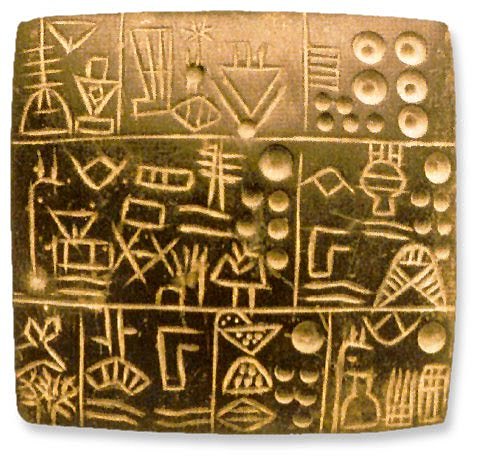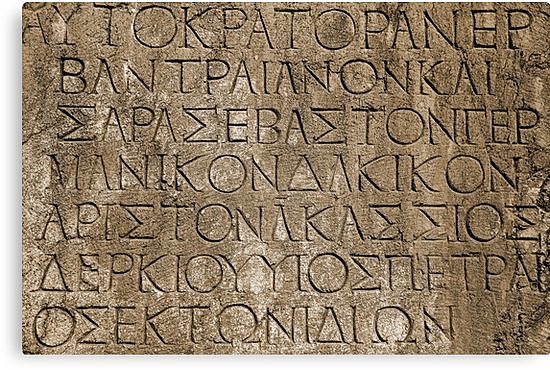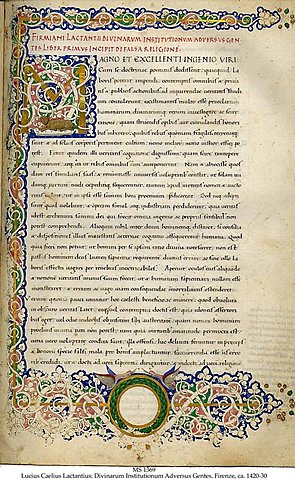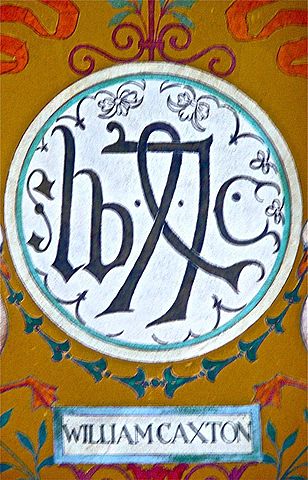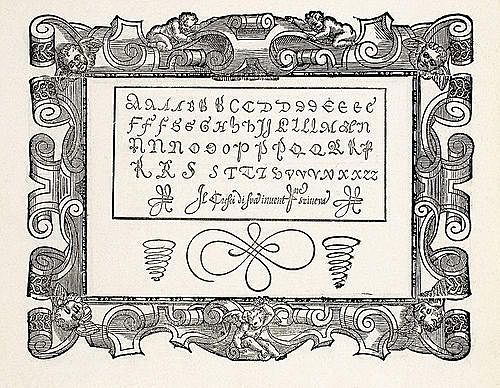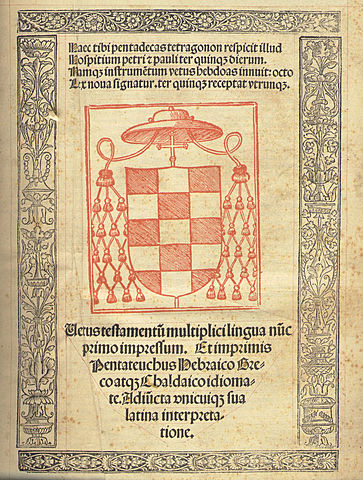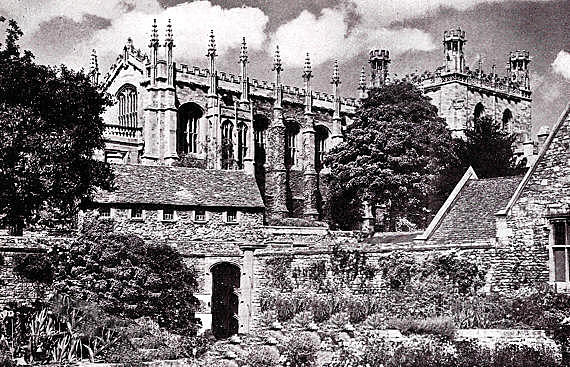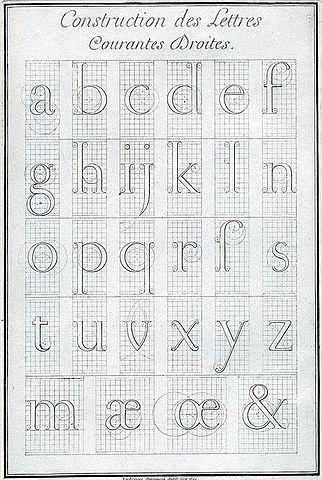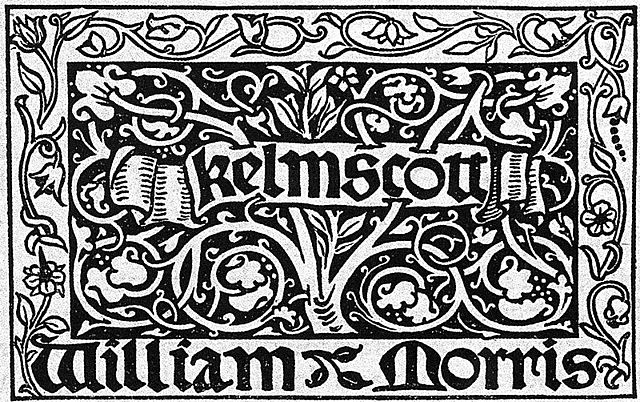
Del latín pictum: relativo a pintar, y del griego grapho: trazar)son grafismos realizados sobre las rocas mediante la aplicación de pigmentos.
es comúnmente aceptada como una de las formas más antiguas de expresión escrita. -
sea una de las manifestaciones artísticas más antiguas que hayan subsistido hasta nuestros días.
Los romanos no inventaron este alfabeto, sino que lo adoptaron de los etruscos, quienes a su vez tomaron las letras del alfabeto griego. Los etruscos contaban con 26 letras en su alfabeto, mientras que los romanos, cuando lo acogieron primeramente, conformaron el suyo con sólo 21.
El sistema de escritura griego es alfabético y tiene su origen c. siglo XI a. C. Señalar que las primeras inscripciones son del siglo VIII a. C. El sentido de la escritura es de derecha a izquierda o en bustrófedon.
Johann Gensfleisch Zum Gutenberg, desarrollo en Alemania una técnica para elaborar moldes de tipos que se utilizarían para la impresión de letras individuales.
Conrad Sweynheym y Arnold Pannartz, establecen la primera imprenta de Italia,
en el Monasterio Benedicto de Subiaco. -
uno de los tipográficos más importantes de la historia por componer "De Praeparatione Evangelica" de Eusebio en 1470, obra que representa el crecimiento del diseño de tipos romanos.
Guillaume Le Roy introdujo la imprenta en Lyon, Francia en 1473; cinco años después se imprime el libro "Le Mirover de la Rédemption", utilizando grabados en madera importados de Basilea.
William Caxton, se imprime el primer libro en ingles titulado "Recuyell of the Historyes of Troye" de Raoul Le Févre.
Aldus Manutius o Aldo Manuzio, fundo su imprenta Aldina en Venecia, en 1494.
Ludovico Vicentino degli Arrighi creó el primer manual de escritura del Siglo XVI. En 1523 publico un segundo manual realizado con bloques de madera, impresas con tipos itálicos que el diseño
reformador de la lengua francesa, su trabajo mas importante fue "Champfleury" publicado en 1529, medita sobre la escritura, proporción y el significado de las letras.
1530 y 1585 las novedades tipográficas tienen su origen en Francia en lo que se denomina Edad de Oro de la tipografía francesa y aparte de ediciones a mano, muestra una creación de tipos verdaderamente interesante
Blado produce y publica "II Perfetto Scrittore" de Giovanni Francesco Cresci, uno de los libros clásicos sobre letras.
El Rey Felipe II de España comiso a Christophe Plantin para que trabajara en la "Biblia Regia", la cual fue impresa en 5 lenguas: hebreo, griego, arameo, latin y siriaco.
Se imprimen los libros de bolsillo clásicos;
Don Quijote de la Mancha, de Miguel de Cervantes.
los tipos que se utilizaron fueron grabados por Christoffel van Dijck de Amsterdam. -
La imprenta de la Universidad de Oxford se establecio en 1667. En 1672 John Fell compro punzones y matrices holandesas.
Luis XIV ordeno la creación de un comité de eruditos para la creación de un nuevo tipo que fuera diseñado bajo principios científicos. Cada letra estaba construida sobre una cuadricula que contenia 2304 cuadros, Philippe Grandjean grabo los punzones
Pierre Simon Fournier el joven, inicio la estandarizacion del tamaño de los tipos al pubicar su "Primera Tabla de Proporciones" en 1737.
Se grabo un tipo etrusco San serif basado en formas de 2000 años de antigüedad, probablemente fue el primer tipo de sans serif que se haya hecho, no eran novedosos, su popularidad se debía a la buena legibilidad y textura.
estaba acargo de la "Stamperia Reale", propiedad de Fernando, Duque de Parma, era el impresor privado de la corte. compro sus primeros tipos y rediseño las formas de las letras romanas.
Robert Thorne fue alumno de Cottrell y exhibio en 1803 por primera vez, letras gruesas, letras cuyo contraste y peso se fue incrementando al aumentar el grosor de sus rasgos fuertes.
Ottomar Mengethaler inventó la linotipia, máquina usada en la composición tipográfica
William Morris fundó la empresa Kelmscott en 1891, su obra mas ambiciosa fue "Los trabajos de Geoffrey Chaucer de 556 paginas, y ocupo 4 años para su elaboración
Otto Eckmann creo uno de los tipos de letra mas originales que se diseño durante el "Art Nouveau", para la findidora Klingspor
publico su libro titulado "Zang Tumb Tumb" en 1914, donde ejemplifica su lema "la palabra en libertad" utilizando nuevas formas tipográficas, enfatizando el contenido del texto.
El Times New Roman se convirtió posiblemente en el tipo mas leido a mediados del siglo, fue diseñado por Stanley Morrison y Victor Lardent para el periodico londinense The Times; esta inpirado en un tipo de Platin del siglo XVIII y se publico en 1932.
Gerard Unger diseñó el tipo Coranto en el 2000. Minion Pro Myriad Pro son revivals hechos en Opent Type por Adobe, e incluyen un gran juego de caracteres para tipos no latinos como griego y cirílico.
fueron un sistema de escritura inventado por los antiguos egipcios. Los antiguos egipcios usaron tres tipos básicos de escritura: jeroglífica, hierática y demótica; esta última corresponde al Periodo tardío de Egipto.
El cuneiforme se escribió originalmente sobre tablillas de arcilla húmeda, mediante un tallo vegetal biselado en forma de cuña, de ahí su nombre.